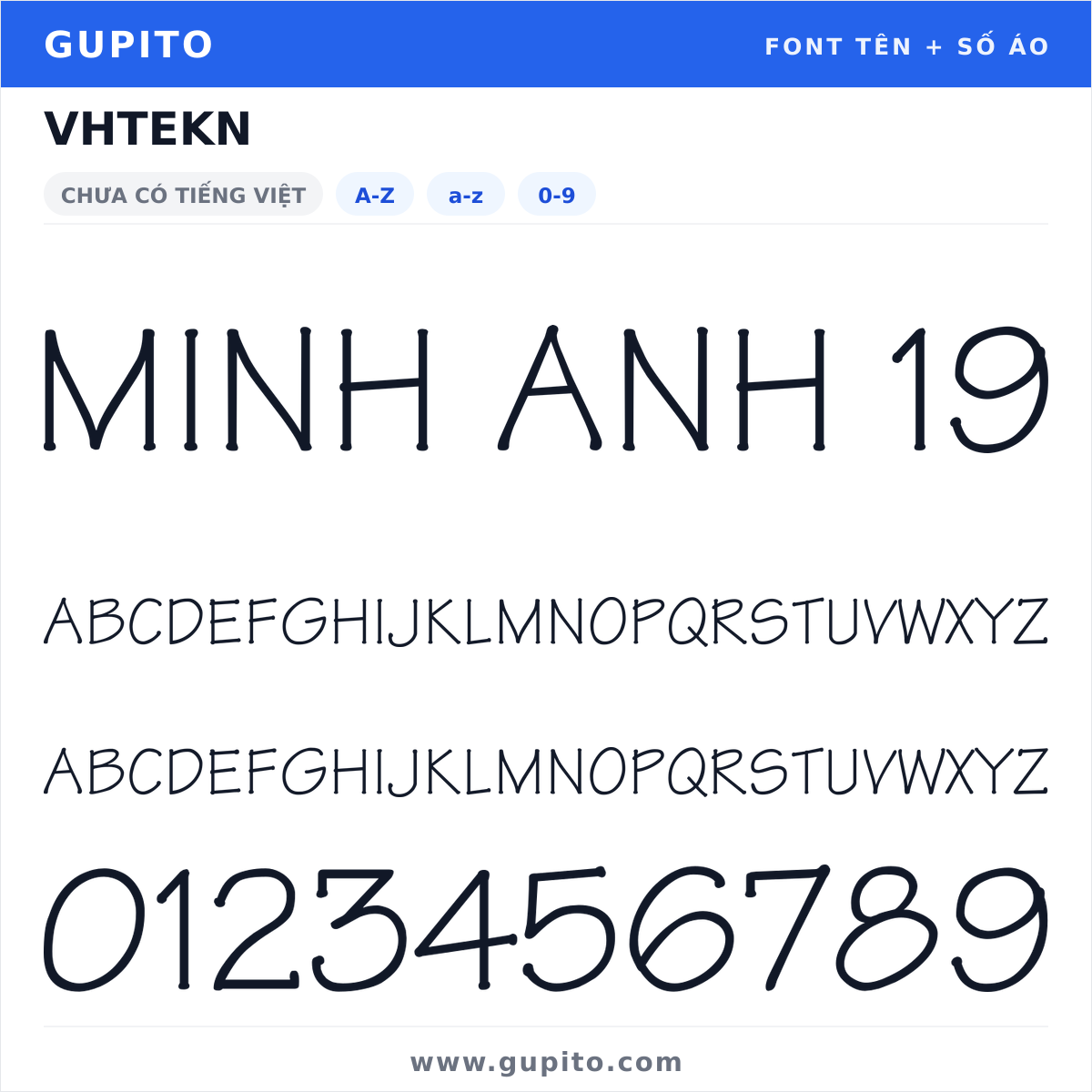
.VnTeknicalH
.VnTeknicalH · Font VHTEKN in tên áo, số áo bóng đá, thể thao · nét mảnh, bo tròn
Font VHTEKN với nét chữ độc đáo, phù hợp in tên, số áo bóng đá, áo lớp, quà tặng. Có bảng số 0-9, chữ thường a-z. Bộ chữ .VnTeknicalH dùng để in chuyển nhiệt lên áo đấu, áo lớp, áo nhóm và đồ thể thao theo yêu cầu. Kiểu dáng: nét mảnh, bo tròn. Font dùng cho chữ không dấu và số áo. Có đủ bộ chữ số để in số áo. Từ khoá liên quan: font vhtekn, font in ten ao, font in so ao, font ao bong da, font the thao, font in chuyen nhiet, font co bang so, font chu thuong.